Nagyon szeretem a karácsonyi készülődést, mert ez aztán a remek alkalom, hogy sokféleképpen kamatoztassuk kalligráfia és akvarell tudásunkat. Több ötlettel is készülök nektek, amit aztán hasznosíthatsz részben vagy egészben, hogy még meghittebbé tedd a karácsonyt. Vágjunk is bele, nézzük meg, hogy ezekhez a karácsonyi ajándékkísérő kártyákhoz mire lesz szükséged:
- olyan 200-300 grammos papír, lényeg, hogy kicsit vastagabb legyen, mint egy normál papír, hogy legyen tartása,
- ceruza a skicceléshez,
- tűhegyű filc, lehetőleg 2 méretben, az én kedvencem a Sakura Pigma Micron toll,
- ecsetfilc (piros, bordó, szürke és zöld),
- olló,
- lyukasztó,
- szalagok, zsinórok.
Az alap
Mindhárom verzióhoz ugyanaz az alapot használjuk, egy 9 cm x 5 cm nagyságú téglalapot. A téglalap csücskeit lekerekítettem van erre egy kis eszközöm, nagyobb kreatív boltban tudsz ilyet vásárolni, de szerintem akár egy ollóval is szépen le tudod kerekíteni. Majd jöhet a lyukasztás egy közönséges irodai lyukasztóval, olyan 0,5 cm-re tettem. És már készen is vagyunk a kártya alapjával, nézzük milyen verziókat tudsz ebből készíteni.
1. verzió – égősorral díszített ajándékkísérő kártya
Nagyon egyszerű, de szerintem nagyon látványos díszítő elem az égősor. Ha biztosra mennél, akkor először használj ceruzát, és aztán rajzold át.
Szóval nincs más dolgod, mint húzz egy hullámos vonalat a téglalap felső harmadában, amit itt-ott megszakítasz egy hurokkal. Majd ezen a vonalon egyenlő távolságra rajzolj kis fekete téglalapokat, egyet az egyik oldalra, majd a másikat a másik oldalra rajzold. Ezek lesznek az égők foglalatai. Érdemes a hurkokon belülre is húzni, úgy még játékosabb lesz! Ha ezzel megvagy, akkor jöhetnek az égők, amit pedig az ecsetfilc hegyével készítesz, úgy, hogy odaérinted az ecsetfilc hegyét, hiszen annak csúcsos formája van, így meg is van az égő formád. A pirosat és a zöldet váltogattam, de persze használhatsz más színeket is, ahogy neked tetszik.
Ezután következhet az írás. Ebben a verzióban a karácsony szócskához modern kalligráfiát használtam, és sima nyomtatott betűt használtam a boldoghoz. Ennek az is volt az oka, hogy így fért el szépen a szöveg és a díszítés. 😅
Ezután jöhet a zsinór, ehhez a verzióhoz egy piros-fehér-zöldet választottam. Egyébként ez közjegyzői zsinór néven fut a papír-írószer boltban. 😁 Ezzel el is készült az első kártya.
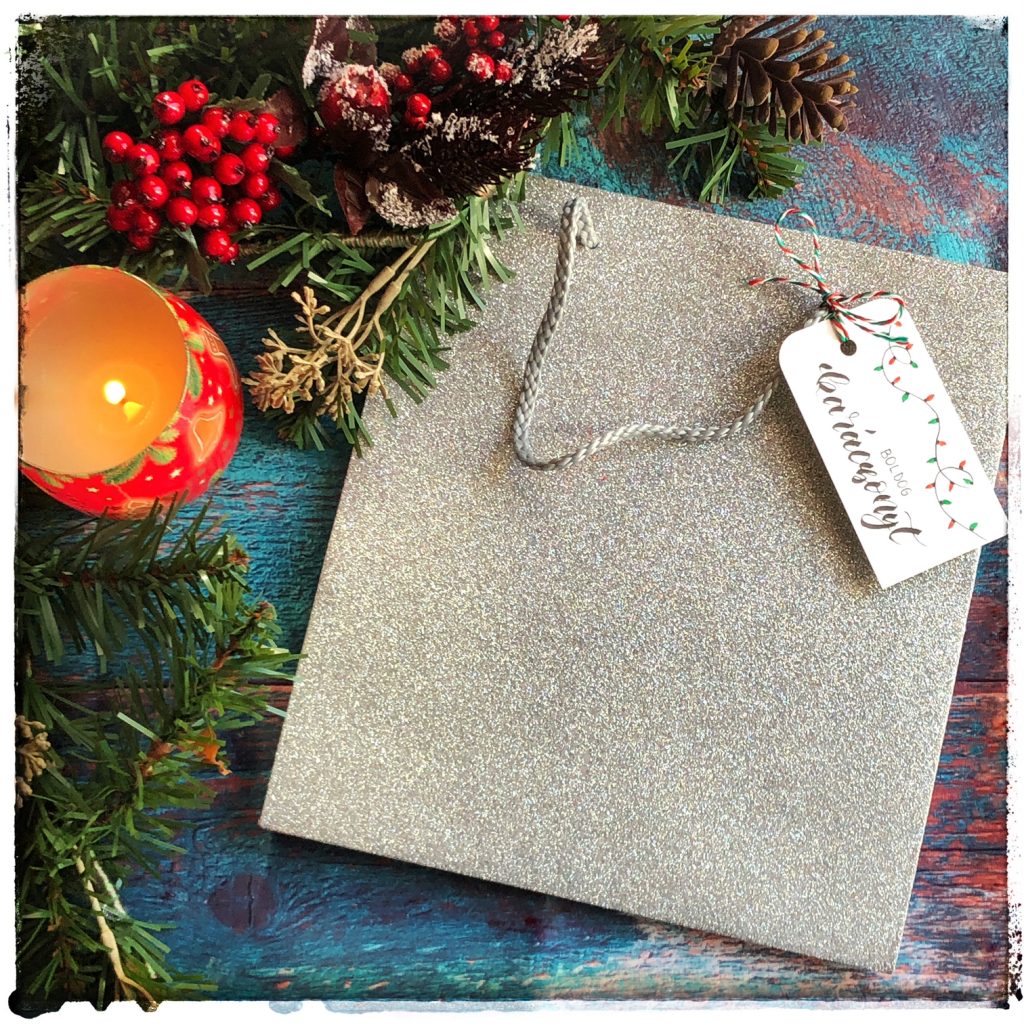
2. verzió – fagyöngyös ajándékkísérő kártya
Ebben a verzióban inkább az íráson van a hangsúly. Szóval érdemes ceruzával egyenest húzni, nekem legalábbis mindig szükségem van rá, mert nem tudok egyenesen írni. 😁 Emellett érdemes a feliratot is felskiccelni, hogy belődd hova szeretnéd tenni a szavakat. Itt a szöveget balra rendeztem, de maga a felirat a kártya közepén van.
Ezért is adódott a jobb felső sarokban egy nagyobb hely, ide fogjuk rajzolni a fagyöngy ágacskát. Nem kell mást tenned, mint húzol egy nagy középső ágat, majd jobb és bal oldalra is húzz egy-egy oldalágat. Figyelj rá, hogy ezek rövidebbek legyenek, mint a főág.
Majd jöhetnek a levelek, amelyek egyszerű hurkok, pont olyan, mint az alapvonásoknál tanult hurkok. Ezeket a leveleket a vastagabb filccel húzd meg, a főerekhez használd a vékonyabbat, mert így szép kontrasztot tudsz létrehozni. A főér ne érjen a levél végéig. Majd a levelek tövében rajzolj kis köröket, azok a „gyöngyök”, akár 2-3-at is. Majd színezd ki a piros ecsetfilccel.
Ezután jöhet a szalag. Ehhez most piros szatén szalagot választottam. A legjobb szalag választék a Flying Tigerben van, vannak egyszínűek és vannak mintásak is.
3. verzió – karácsonyi manós ajándékkísérő kártya
Ez talán kicsit nehezebb lesz, de hidd el, hogy nagyon egyszerű egy ilyen manó rajzolása. Ha még kezdő vagy, akkor érdemes 3 formára lebontani. A nózival szoktam kezdeni, mert kb. az a közepe. Ez egy ovális, aztán az ovális közepétől húzz felfelé egy 3 szöget, ebből alakítjuk ki a sapkáját, alulra pedig egy téglalapot ez lesz a teste. Természetesen ehhez a ceruzát használd először (1. lépés a képen)
Nézzük a sapit! A háromszögnek az orránál lévő sarkait kerekítsd le. Aztán a háromszög közepéig rajzolj egy „hasat” , majd jöhet a bojt. Egy kisebb és egy nagyobb horog, ami végül össze ér. (2. lépés a képen)
A sapi végében rajzolj egy bojtot, ami cikk-cakk vonal egy kör mentén. Jöhet a szakáll, ez is nem más, mint egy cikk-cakk vonal. Csak arra ügyelj, hogy az elején kisebbek legyenek a cikk-cakkok, aztán a test közepe felé legyen hosszabb. A cipők a téglalap alján 2 félkör. szerintem már látod a kismanó körvonalait, szóval nincs más hátra, mint körbe rajzolni a filccel. (3. lépés a képen)
Ezután következhet a színezés. A sapi és a cipő bordó, a test pedig szürke. Többit (szakáll, bojt, nózi), meg simán üresen hagyod. Elkészült az első manód. 😉 Ez egy alap verzió, de lehet játszani minden elemével, talán csak fix a nózi, az mindig nagy és ovális. A sapi, cipő és test megrajzolására végtelen verzió van.
Ehhez most egy zöld raffia szalagot használok kötőnek.
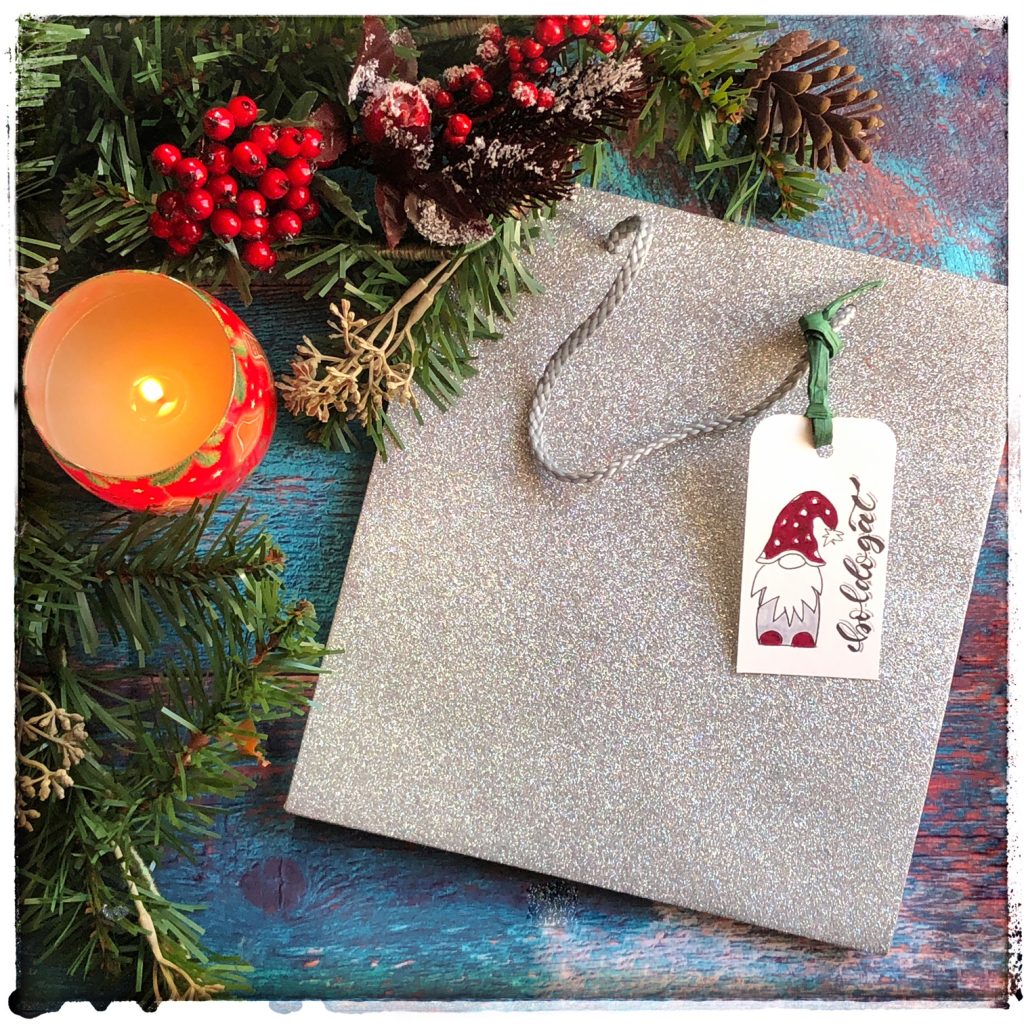
+ 1 verzió